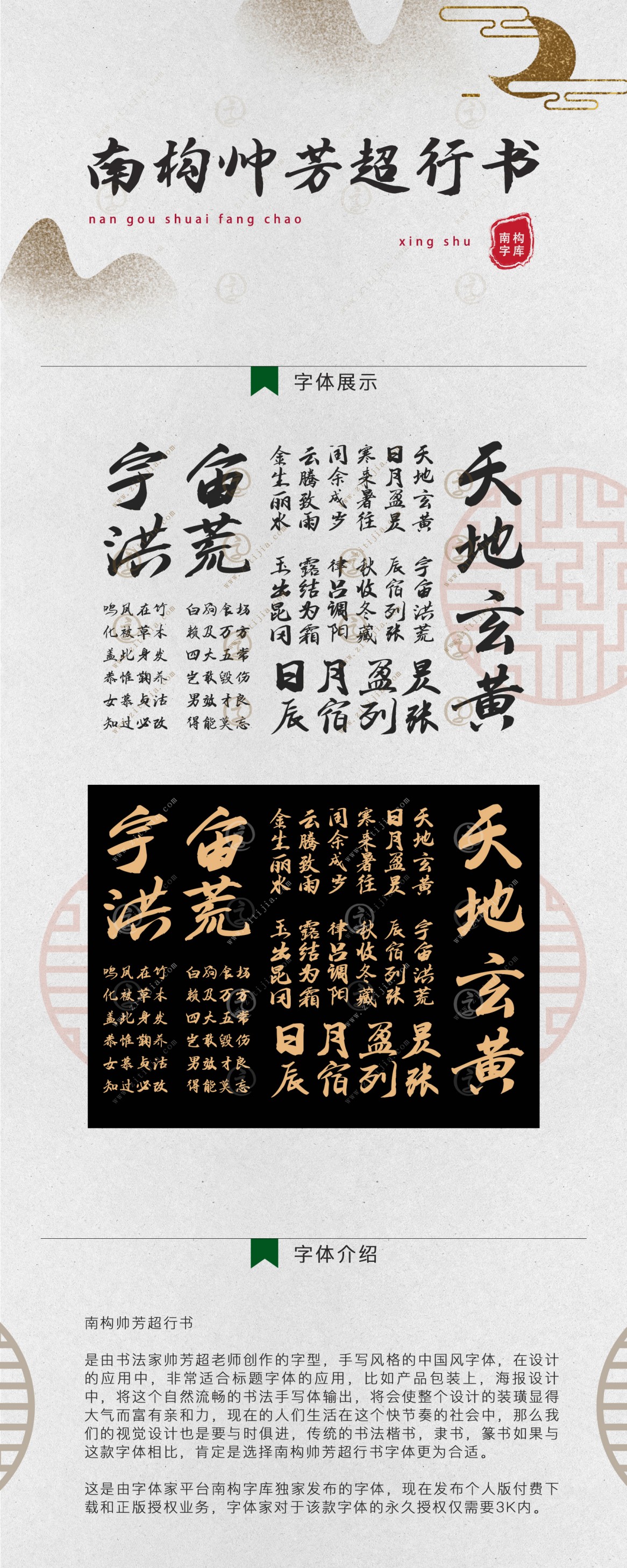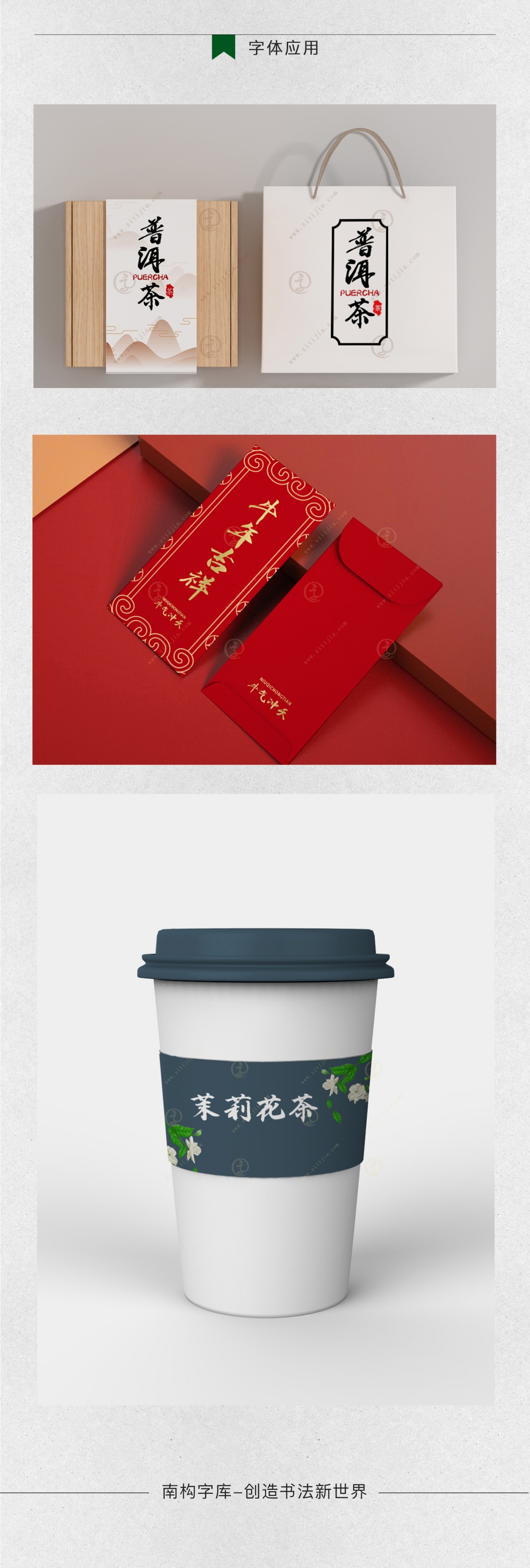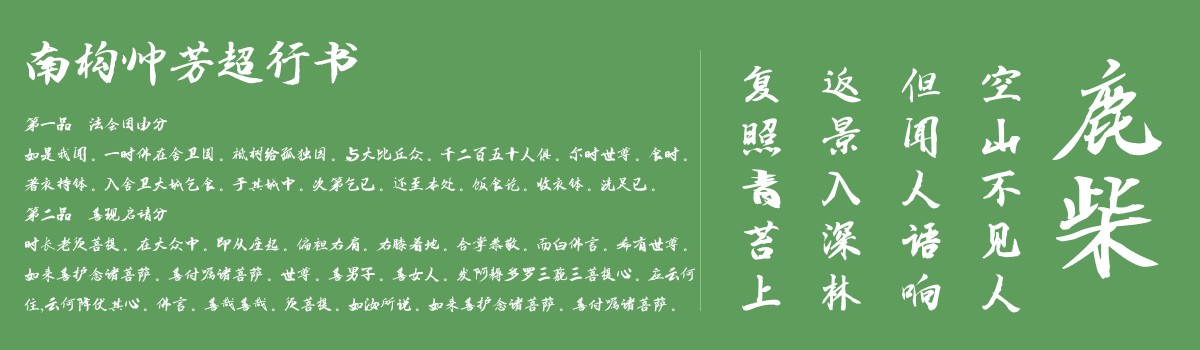
是由书法家帅芳超老师创作的字型,手写风格的中国风字体,在设计的应用中,非常适合标题字体的应用,比如产品包装上,海报设计中,将这个自然流畅的书法手写体输出,将会使整个设计的装璜显得大气而富有亲和力,现在的人们生活在这个快节奏的社会中,那么我们的视觉设计也是要与时俱进,传统的书法楷书,隶书,篆书如果与这款字体相比,肯定是选择南构帅芳超行书字体更为合适。